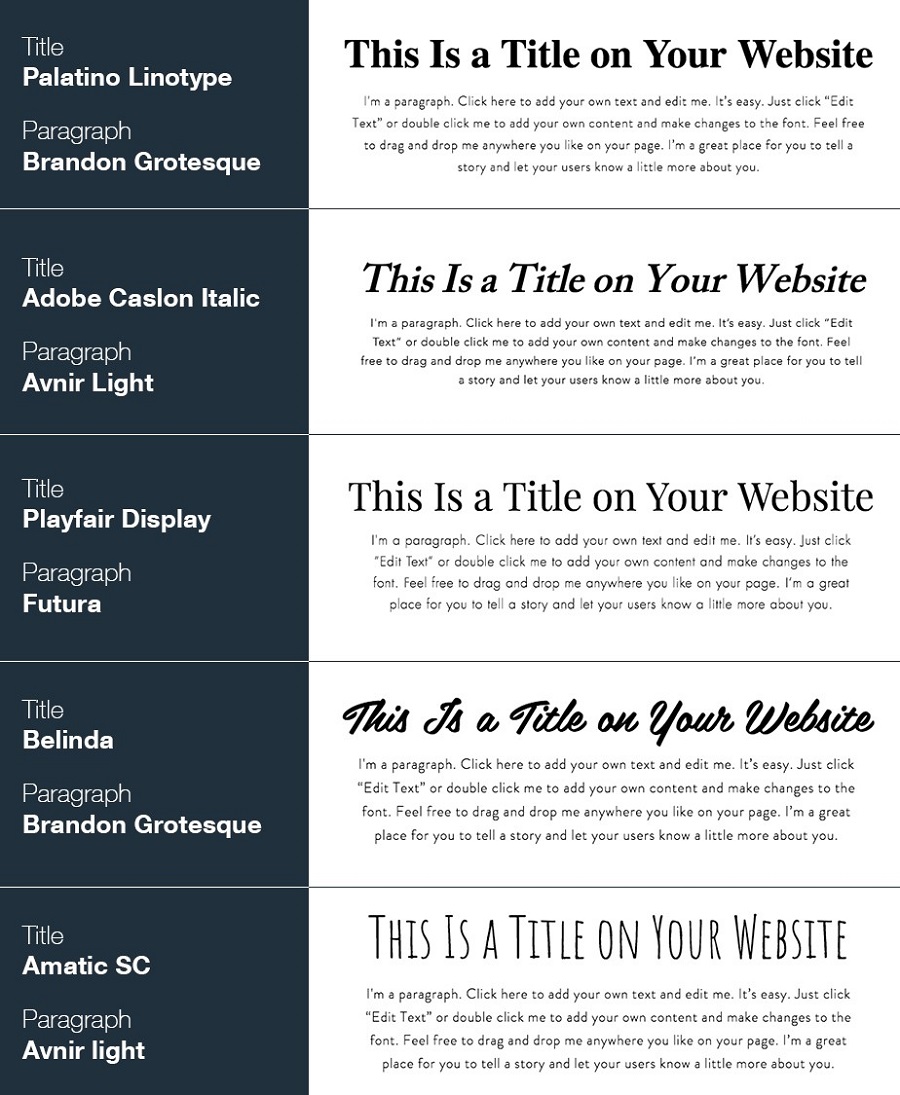
Các thiết kế trang web có rất nhiều điểm cần lưu ý như việc viết nội dung cho bạn, chọn hình nền hay đảm bảo các kết nối truyền thông xã hội,...Thế nhưng có một yếu tố đang bị bỏ quên rất nhiều đó chính là phông chữ. Hãy cùng Viện Công nghệ thông tin ITPlus tìm ra cách chọn font chữ phù hợp cho các thiết kế website nha!
Đảm bảo phông chữ phù hợp với tông màu của thương hiệu
Phông chữ của website cần phù hợp với danh tính của thương hiệu. Bạn không thể đi theo xu hướng nếu nó không phù hợp với những mô hình mà bạn đang gây dựng cho trang web của mình.
Xếp hạng phông chữ của bạn theo mức độ quan trọng
Ngoài ra, các nhà thiết kế cũng không nên sử dụng nhiều hơ ba phông chữ trên trang web của mình. Mặt khác, mỗi phông chữ còn có nhiều mức độ quan trọng khác nhau. Tương tự với khi chọn màu, quá trình này cũng bao gồm việc tìm màu chính, màu phụ và màu nhấn.
Phông chữ chính
Là phông chữ dễ thấy nhất và thương được sử dụng trên tiêu đề trang web của bạn và dễ được nhận dạng nhất với thương hiệu của bạn ngay cả khi nó không được sử dụng nhiều nhất trên trang web của bạn.
Phông chữ phụ
Là phông chữ được sử dụng trong phần lớn các đoạn văn, mô tả, bài viết trên trang web,... Nếu phông chữ chính được dùng để hấp dẫn người xem thì phông chữ phụ sẽ giúp người xem dễ đọc.
Dưới đây là những phông chữ thiết kế đang được ưa chuộng hiẹn nay:
Phông chữ Serif
Là phông chữ thường được sử dụng trong các bản in như sách vở, báo chí,.... Đối với phông chữ, dòng này có thể được tô điểm theo nhiều cách khác nhau để tạo nên những giao diện độc đáo riêng. Phông chữ này cũng thiên về cổ điển và thanh lịch, thường được sử dụng cho những độc giả lớn tuổi hơn.
Phông chữ Sans serif
Là phông chữ dành cho giới trẻ, phù hợp cho màn hình máy tính và điện thoại thông minh. Đây là lý do phông chữ này được sử dụng hầu hết trên các trang web hiện nay.
Nắm vững nghệ thuật pha trộn phông chữ
Ngoài việc tự tạo ra những font chữ độc đáo cho các thiết kế của riêng mình, bạn cũng có thể dê dàng tải những phông chữ trên các trang web hiện nay và hòa trộn chúng trong các thiết kế của riêng mình.
Biết trọng lượng (và kích thước) của các từ của bạn
Khi nói đến font chữ, điều tiếp theo chúng ta cần để ý tiếp nữa đó chính là kích thước font chữ. Bạn cần thiết kế kích thước font chữ sao cho phù hợp với tiêu đều, phụ đề hay văn bản đoạn. Dưới đây là một gợi ý cho các bạn tham khảo về kích thước font chữ:
Kích thước của các phông chữ ở đầu trang cần được nhấn mạnh bằng cách in đậm, in nghiêng hay gạch dưới. Tuy nhiên việc sử dụng quá nhiều cách nhấn mạnh này có thể làm mất phong cách của font chữ gốc.